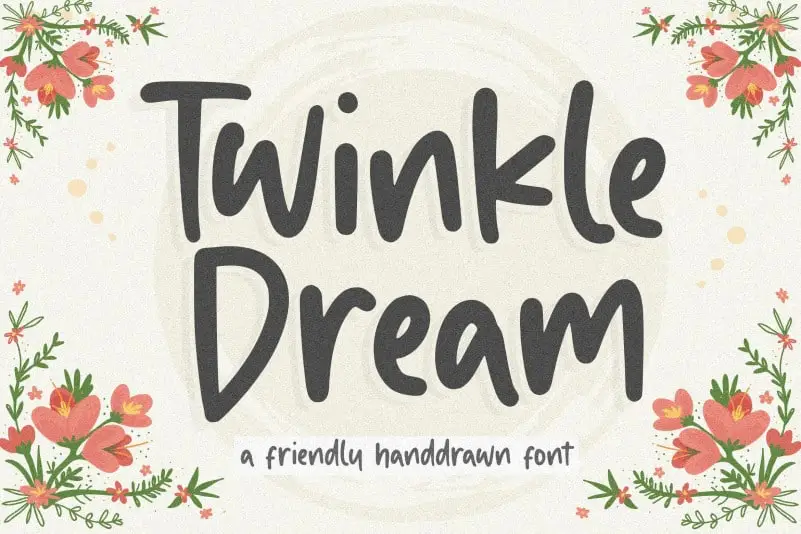
Twinkle Dream Handdrawn Font – Download Grátis
A Twinkle Dream Handdrawn Font é uma delicada escolha para aqueles que procuram um estilo elegante e autêntico na hora de projetar seus produtos ou marcas. Ela tem a capacidade de se destacar em muitas aplicações, desde embalagens de produto até materiais de marca, jornais, mídias sociais, cartões-de-cabimento para casamentos ou simplesmente qualquer frase que você gostaria de destacar acima de um fundo. A Twinkle Dream traz uma sensação delicada e elegante, com traços suaves e detalhes atraentes que vão se encaixar perfeitamente em uma variedade de estilos de design gráfico, tornando-a uma opção ideal para quem quer transmitir emoção e personalidade em suas criações. Sua natureza autêntica e delicada fazem dela um recurso inconfundível para designers que buscam adicionar um toque único e charmoso a seus projetos visuais.